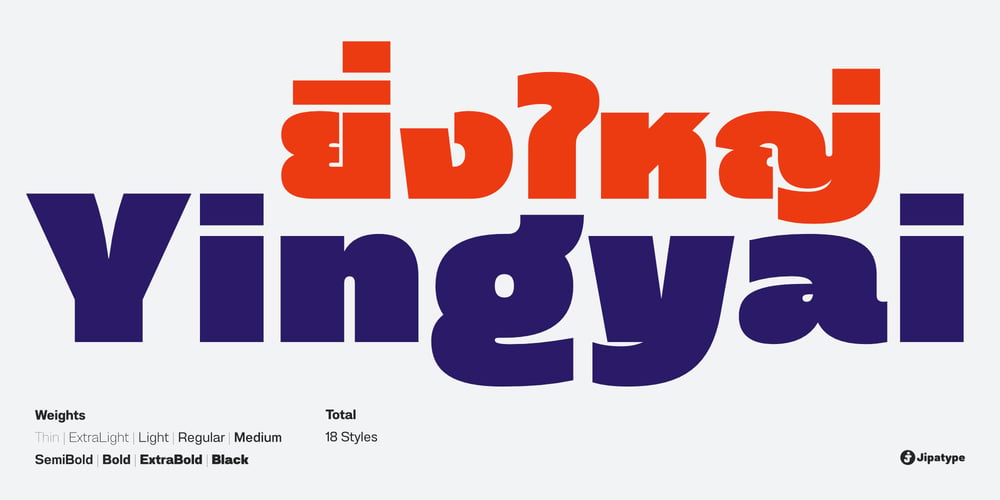
Yingyai Font Family was designed by Anupap Jaichumnan and published by Jipatype. Yingyai contains 18 styles and family package options. ฟอนต์ยิ่งใหญ่ เป็นอักษรแบบแซนเซอริฟ ที่มีความหนาของเส้นมากว่าปกติ สังเกตุได้จากน้ำหนัก Black ให้ความรู้สึกหนักแน่น หนา ใหญ่ และ ทันสมัย มีทั้งหมด 9 น้ำหนักและตัวเอียงของแต่ละน้ำหนักรวมทั้งหมดมี 18 สไตล์ รองรับหลากหลายภาษา เหมาะสำหรับการใช้ผาดหัว ป้าย เนื้อความ ฟอนต์ยิ่งใหญ่สามารถช่วยส่งเสริมให้งานของคุณดูสะดุดตาอย่างยิ่ง เหมาะกับผู้ที่ต้องการให้โฆษณาสินค้าและบริการดูสะดุดตากว่าใคร ๆYingyai is a sans serif typeface with a large line stroke thickness more than usually, especially Black weight. It gives a heavy, big and modern feel. Comes with 9 weights and italics of each weight total 18 styles. Support multi-languages. Suitable for headline, sub-headline or text body. Yingyai can make your work more eye-catching, for those who want to advertise products and services more eye-catching than others.